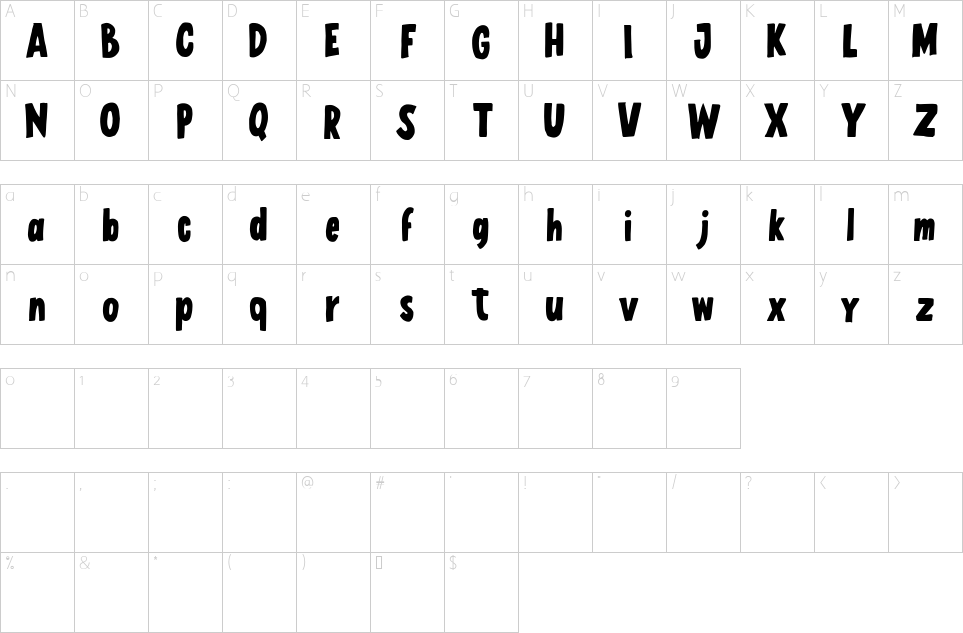
A Mayasi Font é uma deliciosa fonte gratuita que surgiu do trabalho inspirador da Inspiratype. Esta fonte é uma delícia para designers e amantes do design gráfico, oferecendo um charme elegante e um pouco de descontração em cada letra. A Mayasi não é apenas uma opção para designers que buscam uma fonte moderna e sofisticada, mas também para quem aprecia um ar de versatilidade na sua composição. Com o design envolvente da Mayasi, a impressão ou a publicação de qualquer projeto ganha um toque de elegância e personalidade. Descubra por si mesmo o encanto da Mayasi e descubra uma fonte que será sua companheira perfeita para qualquer projeto. Como uma fonte gratuita, a Mayasi está aqui para oferecer uma maneira incrível de manter seu design sempre atualizado e acessível.